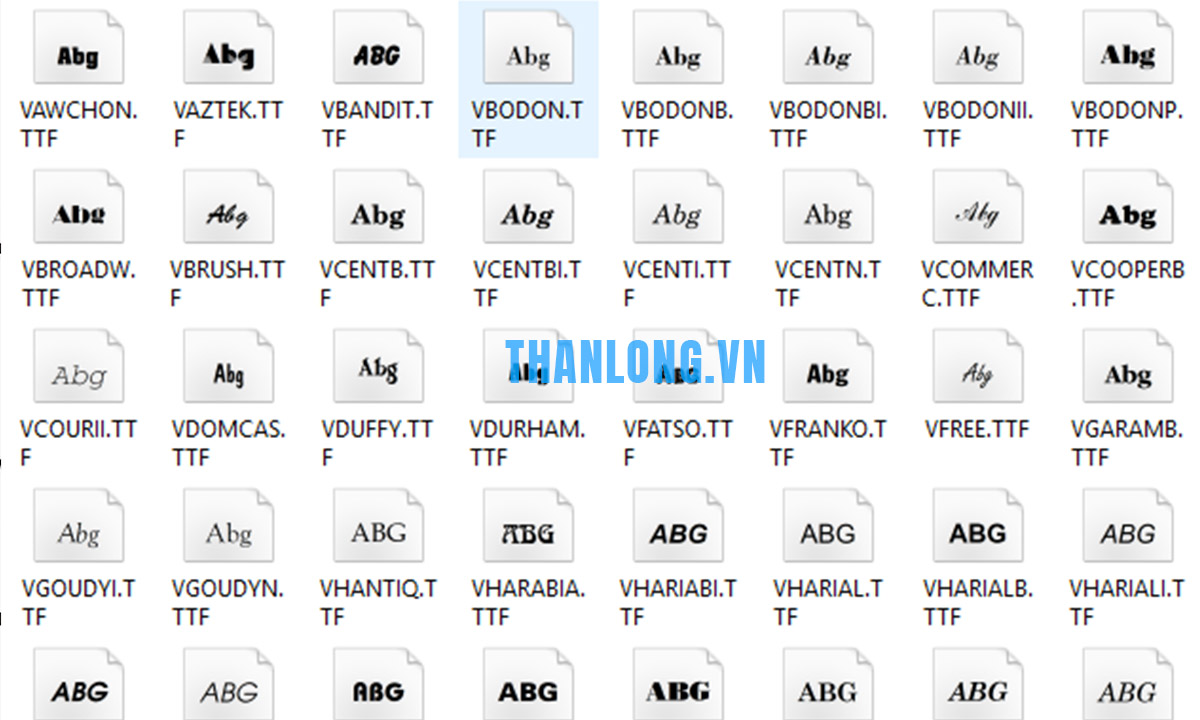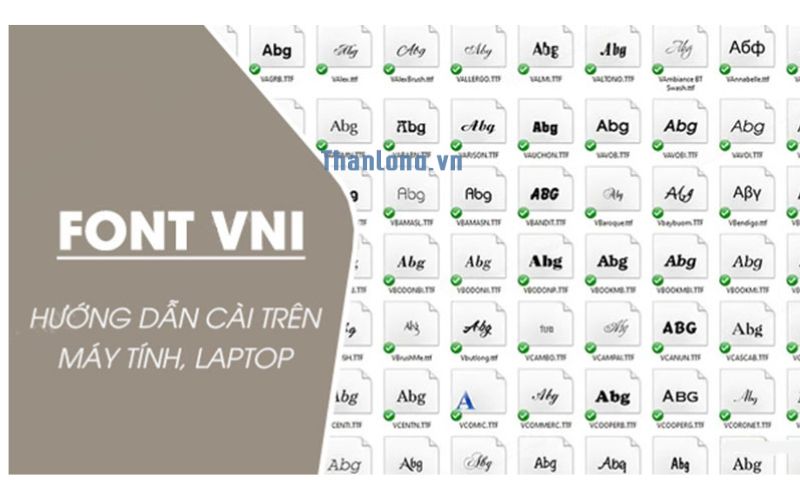
Font VNI là gì?
Font VNI là bộ phông chữ phổ biến, giúp soạn thảo tiếng Việt chuẩn và không lỗi font trên máy tính. Với hơn 300 kiểu chữ đa dạng. Bộ font này hỗ trợ tối ưu cho công việc văn bản, thiết kế đồ họa và chat trên nhiều phần mềm. Không chỉ đơn thuần là phông chữ tiếng Việt. Font VNI còn mang đến nhiều kiểu dáng đẹp. Dễ dùng và đặc biệt hỗ trợ đầy đủ dấu tiếng Việt. Nhờ vậy, bạn có thể yên tâm soạn thảo. Đảm bảo không lo lỗi font trên Photoshop, Proshow Producer hay các ứng dụng khác.
Một điểm cộng lớn KHI tải font vni times là khả năng tương thích cao với nhiều phần mềm phổ biến như Microsoft Word, Photoshop, Proshow Producer, hay các ứng dụng chat trực tuyến. Nhờ vậy, bạn tránh được các lỗi font chữ thường gặp khi làm việc với tiếng Việt có dấu. Giúp tiết kiệm thời gian và nâng cao hiệu quả công việc.
Font VNI được xem là font chữ gõ tiếng Việt phổ biến nhất hiện nay. Khi tải font vni-times này bạn có thể dễ dàng gõ tiếng Việt trên tất cả những ứng dụng soạn thảo văn bản phổ biến. Ví dụ như một số ứng dụng như Zalo, Skype,…
Công dụng của việc tải font chữ vni
Ngoài việc tải font vni avo  để hỗ trợ cho việc gõ tiếng Việt, thì font chữ này còn cung cấp những font chữ phổ biến nhất trong văn bản. Bao gồm 300 kiểu khác nhau. Nhờ vậy, bạn có thể sử dụng thoải mái lựa chọn những font chữ đa dạng để hỗ trợ cho việc thể hiện văn bản phong phú và sinh động hơn. Việc sử dụng font chữ VNI để loại bỏ những vấn đề lỗi trong việc đánh máy bạn nhé!
Tuy nhiên, nếu bạn yêu thích những chữ viết dạng thư pháp, thì bộ font VNI hoàn toàn có thể giúp đỡ bạn thực hiện vấn đề này. Với 300 font chữ 300 chữ kiểu dáng đa dạng, phù hợp với nhiều đối tượng sử dụng hơn. Nhờ đó, khi bắt đầu thực hiện văn bản, bạn sẽ chọn được một font đúng với nhu cầu bản thân mong muốn.
Đặc điểm nổi bật của bộ phông VNI
• Hỗ trợ tiếng Việt đầy đủ: Bộ font VNI bao gồm tất cả các ký tự có dấu tiếng Việt. Giúp soạn thảo chuẩn xác, không lỗi font.
• Đa dạng kiểu chữ: Với hơn 300 kiểu chữ khác nhau.Từ cổ điển đến hiện đại. Phù hợp với nhiều phong cách thiết kế và nhu cầu sử dụng.
• Tương thích cao: Hoạt động mượt mà trên hầu hết các phần mềm phổ biến như Microsoft Word, Photoshop, Proshow Producer và nhiều ứng dụng khác.
• Đẹp mắt và chuyên nghiệp: Các kiểu chữ được thiết kế tỉ mỉ. Giúp văn bản và thiết kế trở nên sinh động, bắt mắt và chuyên nghiệp hơn.
• Phù hợp đa dạng mục đích: Từ soạn thảo văn bản. Thiết kế đồ họa đến làm video hay chat trên các nền tảng, VNI đều đáp ứng tốt.
Lợi ích việc tải font vni đầy đủ
• Hỗ trợ hơn 300 phông chữ khác nhau,. Có cả kiểu chữ thư pháp và rất nhiều font chữ đẹp mắt khác.
• Sử dụng font chữ nhẹ nhàng thân thiện được thiết kế đẹp mắt phù hợp mọi loại văn bản word.
• Khả năng tương thích với hầu hết các hệ điều hành khác nhau.